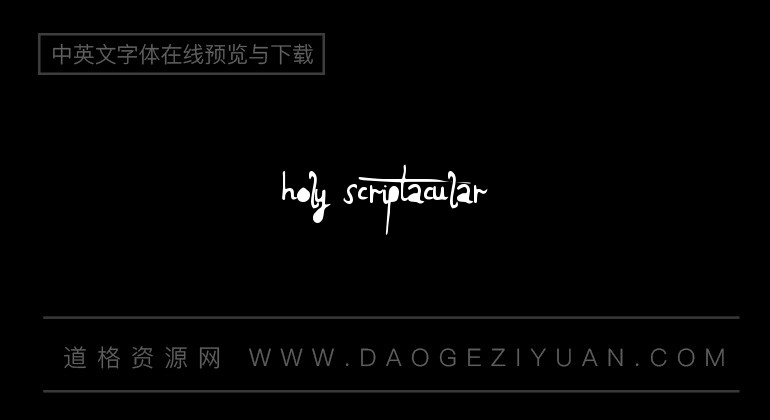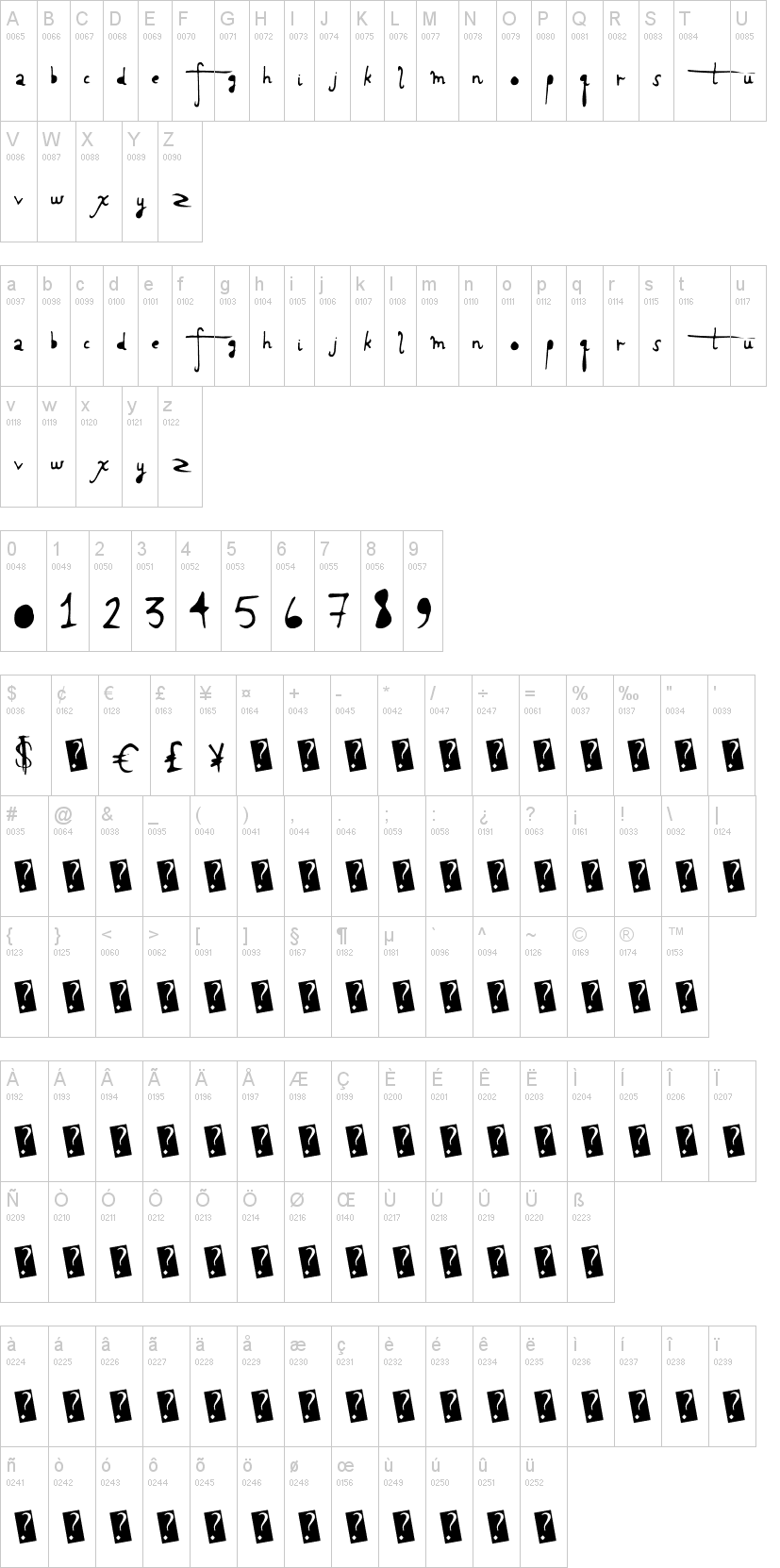
Holy Scriptacular字体是一款美丽的草书字体,它拥有优雅而精致的设计,适用于各种不同的场景,从标题到卡片,从海报到礼品。Holy Scriptacular字体具有清晰的曲线,细节十分丰富,可以帮助您创造出精致而独特的设计。此外,它还支持多种语言,可以让您的设计更加具有国际化的视觉效果。内容介绍
Holy Scriptacular是一款非常不错的手写艺术字体,具有很好的视觉感,适合于文化类的宣传设计、商业类品牌的广告和产品包装设计以及个性化文字排版等较多场景。